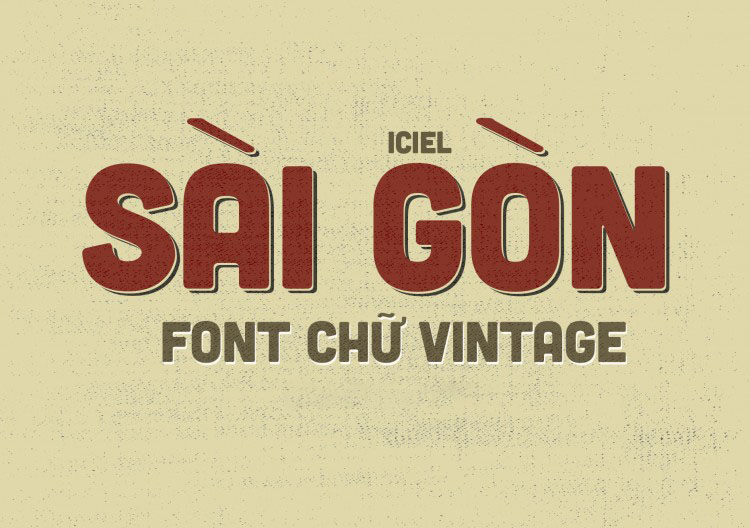
Tải font iCiel là lựa chọn quen thuộc của nhiều designer nhờ sự đa dạng về kiểu chữ và khả năng hỗ trợ tiếng Việt tốt. Tuy nhiên, nhiều người khi download font iciel từ internet lại gặp tình trạng font thiếu ký tự hoặc chưa được việt hóa hoàn chỉnh. Điều này khiến chữ hiển thị sai dấu hoặc không thể sử dụng trong thiết kế. Trong bài viết này, Xưởng In Viva tổng hợp các bộ tải font iciel việt hóa phổ biến và dễ sử dụng trong thiết kế cũng như in ấn.
Tổng hợp các bộ tải font iCiel được sử dụng phổ biến
Thư viện font của iCiel khá đa dạng, từ font serif cổ điển đến font display hiện đại. Nhờ vậy, designer có thể dễ dàng lựa chọn font phù hợp cho từng phong cách thiết kế khác nhau.
Dưới đây là một số font nổi bật khi tải font iciel được sử dụng nhiều trong thiết kế:
| Font | Phong cách | Ứng dụng | Hỗ trợ tiếng Việt |
|---|---|---|---|
| iCiel Cadena | Serif | Thiết kế sang trọng | Có |
| iCiel Crocante | Script | Logo, branding | Có |
| iCielBC Cubano | Display | Poster, tiêu đề | Có |
| iCiel Bambola | Handwritten | Thiết kế sáng tạo | Có |
Vì sao tải font iCiel được nhiều designer lựa chọn?
Không phải ngẫu nhiên mà tải font iciel lại được tìm kiếm nhiều trong cộng đồng thiết kế. Bộ font này nổi bật nhờ sự đa dạng phong cách và khả năng ứng dụng linh hoạt trong nhiều loại dự án.
Nhiều designer sử dụng download font iciel cho các dự án thiết kế logo, poster hoặc bao bì sản phẩm nhờ nét chữ rõ ràng và dễ tạo điểm nhấn.
06 nhóm font iCiel phổ biến theo từng nhu cầu thiết kế
Thư viện font iCiel bao gồm nhiều nhóm khác nhau, mỗi nhóm phù hợp với một phong cách thiết kế riêng.
- Font serif: phù hợp thiết kế thương hiệu cao cấp.
- Font sans-serif: phù hợp thiết kế hiện đại.
- Font display: dùng cho poster hoặc tiêu đề.
- Font handwritten: tạo cảm giác cá nhân và sáng tạo.
- Font script: phù hợp thiết kế mềm mại.
- Font vintage: dùng trong thiết kế retro.
Nhờ sự đa dạng này, tải font iciel việt hóa giúp designer dễ dàng chọn font phù hợp cho từng dự án.
Ứng dụng của tải font iCiel trong thiết kế thực tế
Nhờ nhiều phong cách khác nhau, download font iciel có thể ứng dụng trong rất nhiều loại thiết kế.
Một số ứng dụng phổ biến gồm:
- Thiết kế logo thương hiệu
- Poster quảng cáo
- Banner truyền thông
- Thiết kế bao bì sản phẩm
- Tiêu đề bài viết hoặc landing page
- Thiết kế nội dung mạng xã hội
Với khả năng hiển thị rõ ràng và thẩm mỹ cao, tải font iciel thường được sử dụng cho cả thiết kế online và in ấn.
03 lưu ý khi dùng tải font iCiel trong thiết kế
Mặc dù font iCiel khá dễ sử dụng, nhưng designer vẫn cần lưu ý một số điểm để đảm bảo thiết kế đạt hiệu quả tốt nhất.
- Chọn font phù hợp phong cách: mỗi font có mục đích sử dụng khác nhau.
- Kết hợp font hợp lý: tránh dùng quá nhiều font trong một thiết kế.
Những lưu ý này giúp việc download font iciel và sử dụng trong thiết kế trở nên hiệu quả hơn.
Tải font iCiel dùng để thiết kế gì?
Font iCiel thường được dùng cho logo, poster, banner và thiết kế branding.
Font iCiel có hỗ trợ tiếng Việt không?
Nhiều font iCiel đã được việt hóa và hỗ trợ đầy đủ dấu tiếng Việt.
Có thể dùng font iCiel cho in logo không?
Hoàn toàn có thể. Font iCiel hiển thị rõ ràng và phù hợp cho nhiều loại thiết kế in ấn.
Tải font iCiel là lựa chọn phổ biến đối với nhiều designer nhờ sự đa dạng về phong cách và khả năng hỗ trợ tiếng Việt tốt. Khi sử dụng đúng phiên bản download font iciel việt hóa, bạn có thể đảm bảo chữ hiển thị chính xác trong các phần mềm thiết kế và giữ được tính thẩm mỹ cho bố cục.